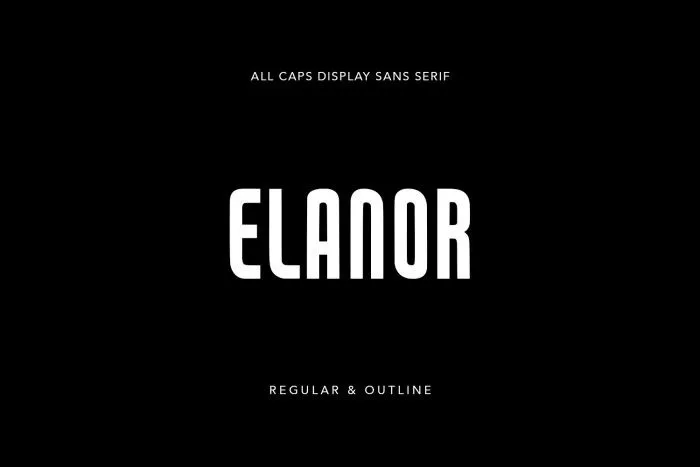
Elanor Display Font – Download Grátis
Elanor Display Font é uma fonte de tipo retro para uso em display, inspirada nas letras aquarelas feitas à mão. Ela apresenta os arquivos dos tipos Outline e Regular, oferecendo um estilo único que se destaca entre as muitas opções disponíveis no mercado. Este design foi criado pelo designer Maulana Creative, que busca trazer uma versão melhorada da famosa fonte Serrona Typeface para o público. Elanor é perfeitamente adaptada para aplicações em várias mídias, como logomarcas, revistas, filmes e websites, bem como para qualquer tipo de utilização gráfica que exija um estilo arrojado e moderno. Esta fonte brilha em headlines, títulos, legenda e até mesmo nas camisetas dos jogos de futebol. Ela oferece uma vasta gama de possibilidades criativas para quem busca dar vida à sua ideia através do design gráfico.